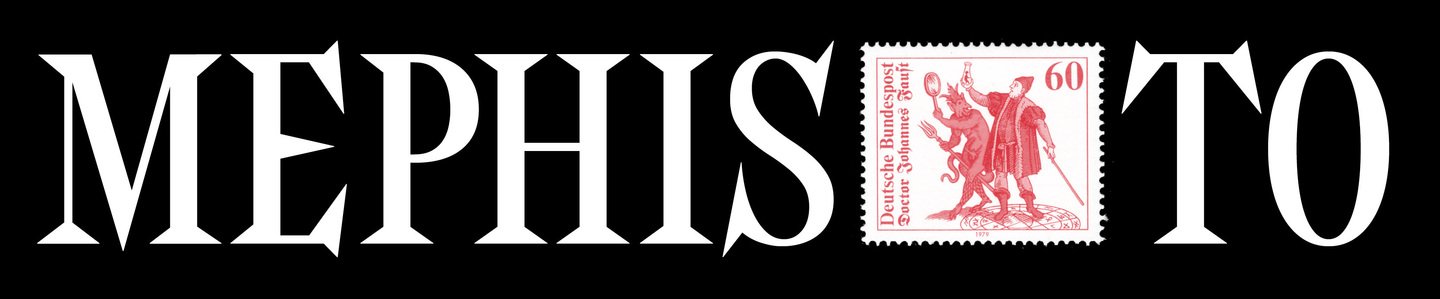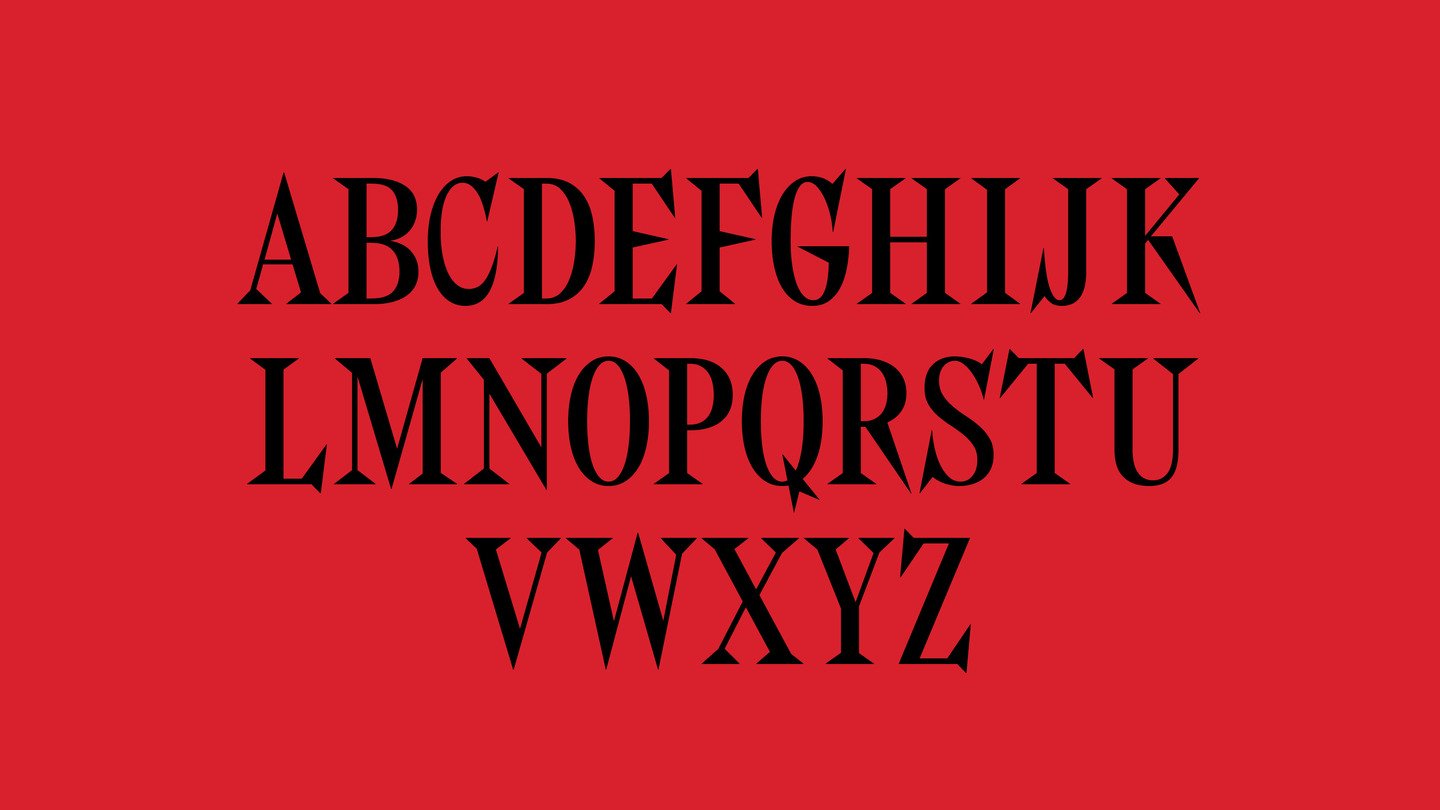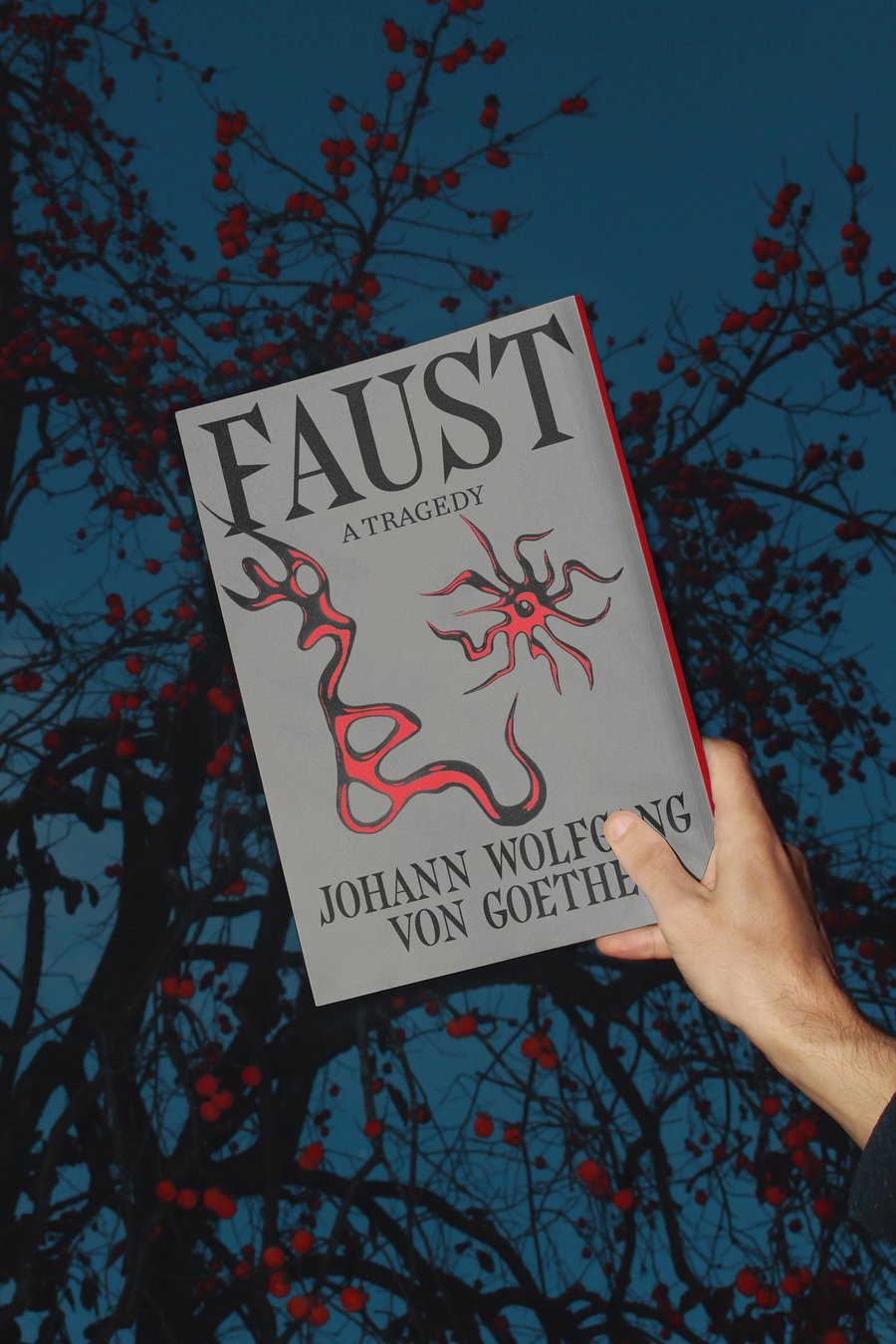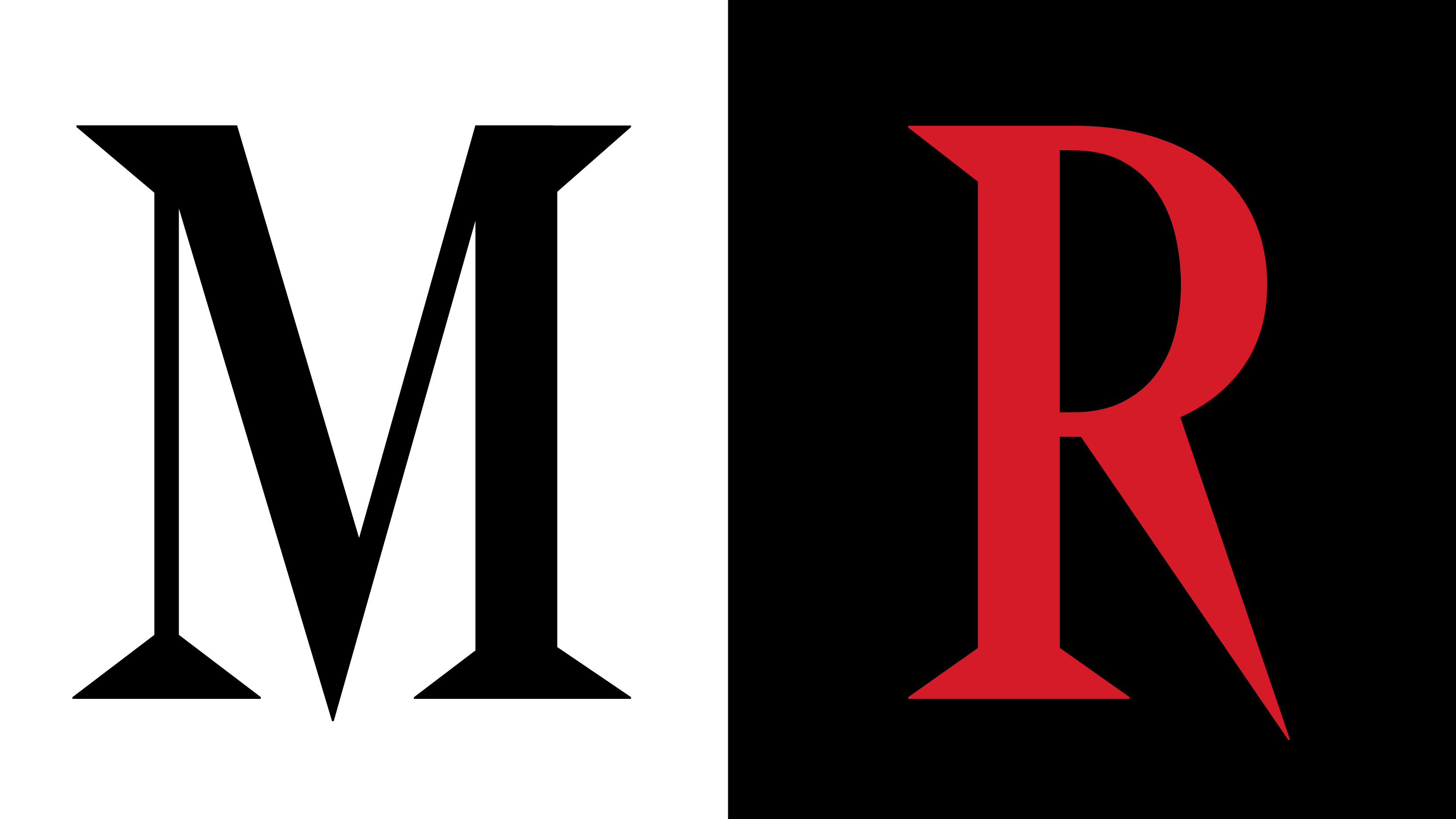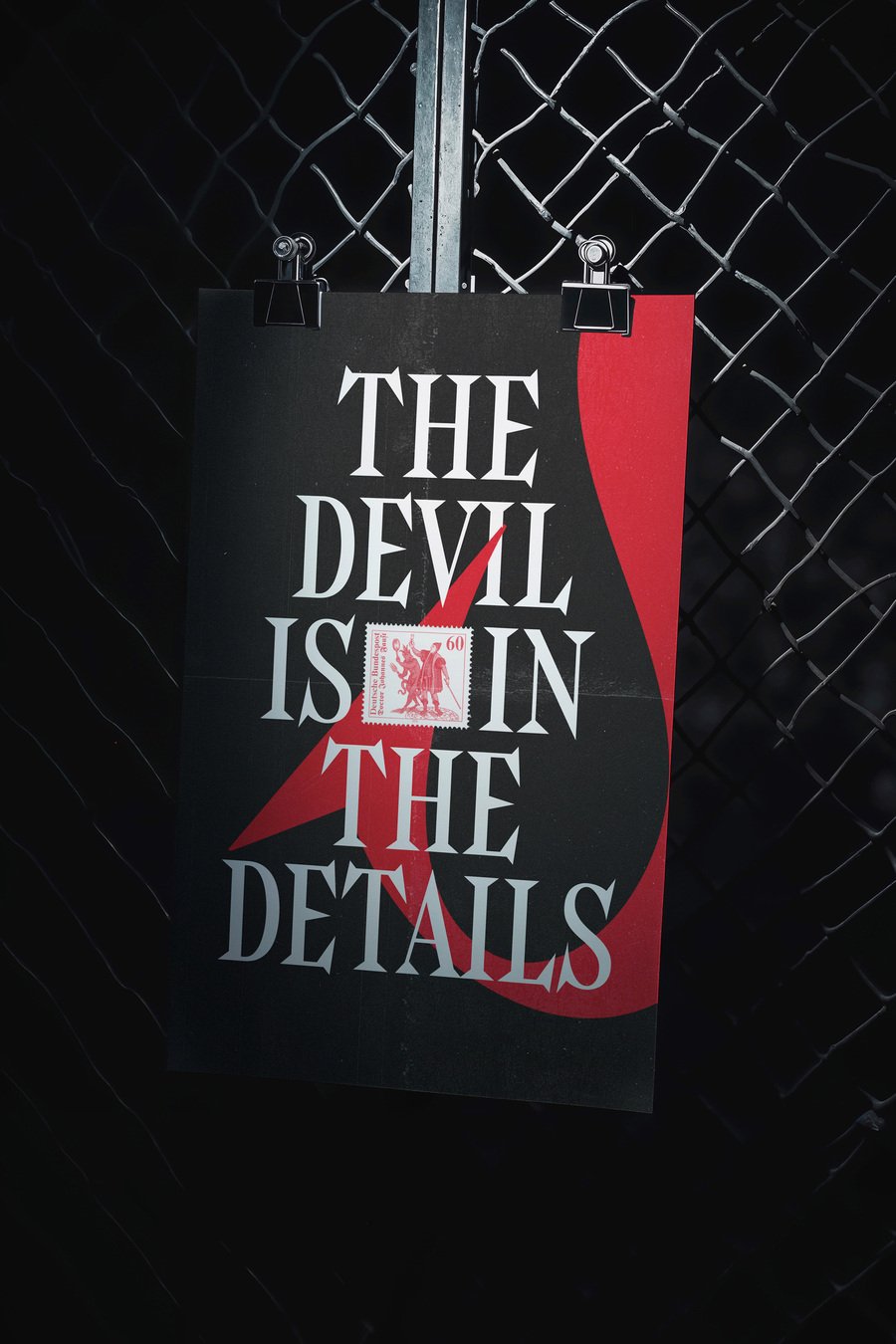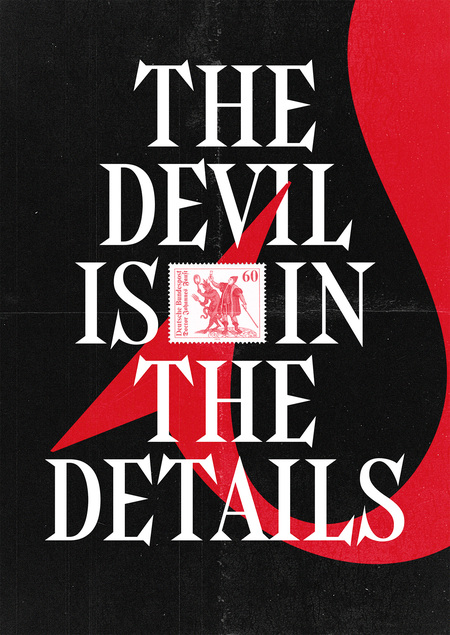
MEPHISTO — акцидентная антиква с ироничным, лукавым характером, названная в честь культового антагониста Гёте, дьявольского трикстера. У шрифта надменно-острые засечки и заостренные терминалы, насыщенное контрастное начертание и зауженные знаки.
Из особенностей шрифта можно отметить динамичный вертикальный ритм, острые засечки «шипы», терминалы в виде дьяволських хвостов и острые апексы со свисаниями.